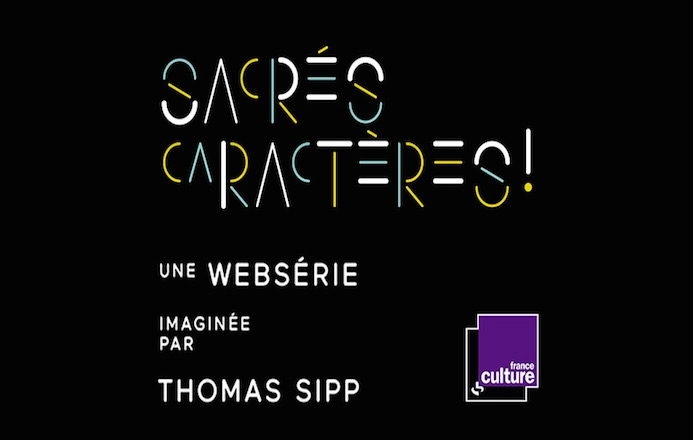
Aussi, nous avons adoré la web série de France Culture "Sacrés Caractères".
Composée de 12 épisodes pour le moment, la série "Sacrés Caractères" fondée par Thomas Sipp nous raconte l'histoire des polices que l'on utilise au quotidien : Futura, Times, Gotham, Comic Sans...
Nous avons particulièrement aimé le mini épisode sur la police Garamond... qui n'est pas sans rappeler la typo du Papier fait de la Résistance n'est-ce-pas ? ;)
La police Garamond est d'ailleurs considérée comme la typographie des gens qui "pensent différemment". ON LE SAVAIT ! ;)